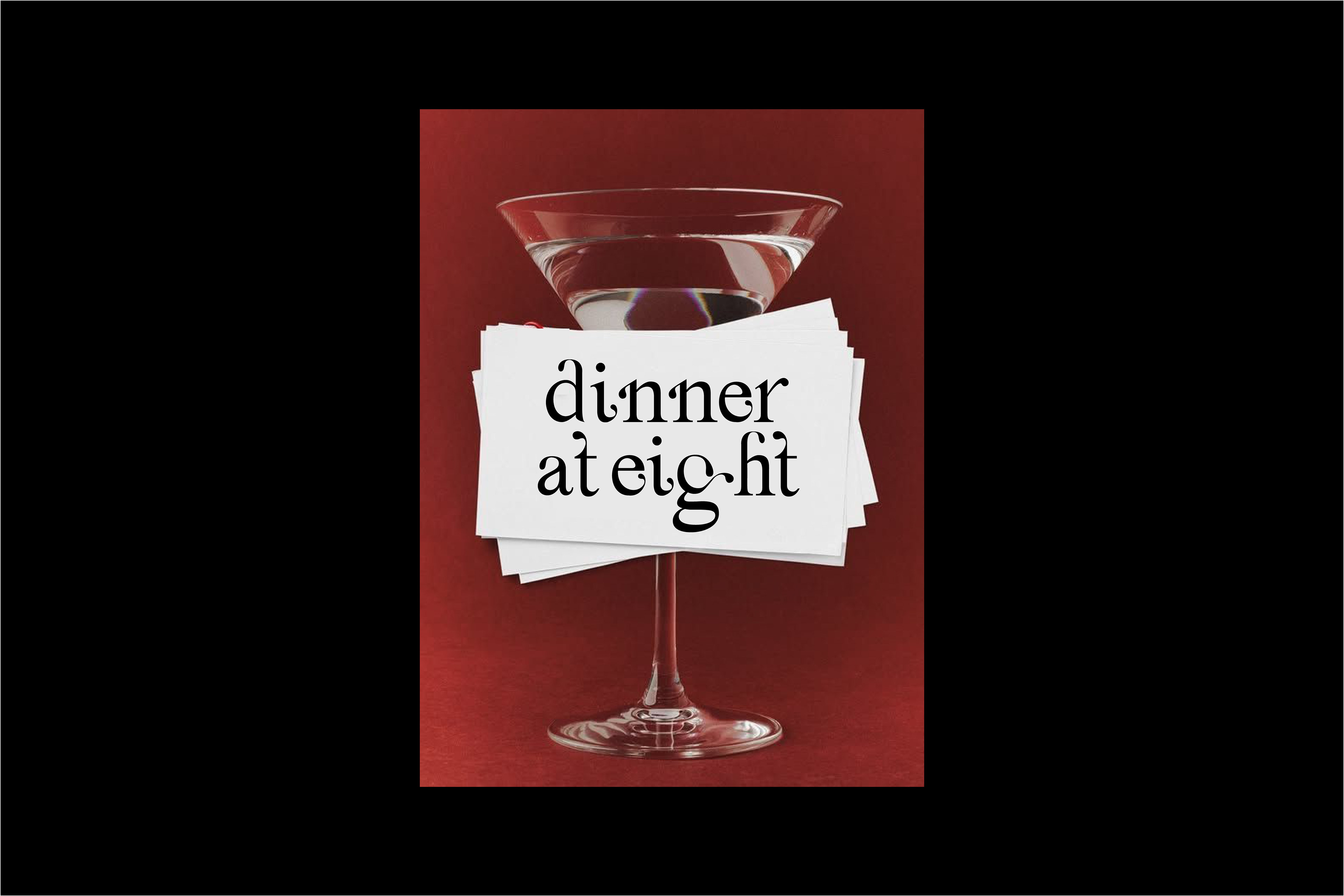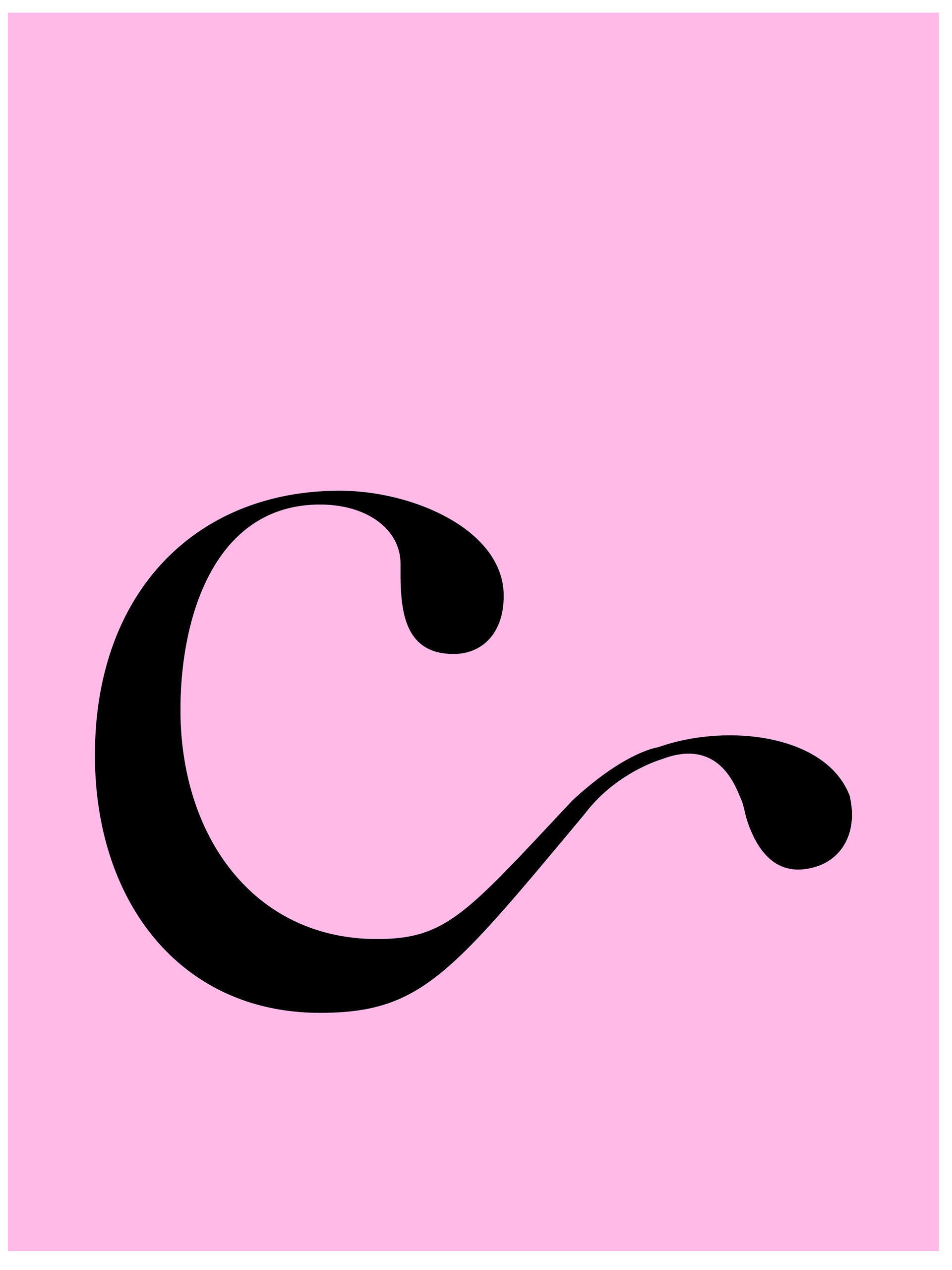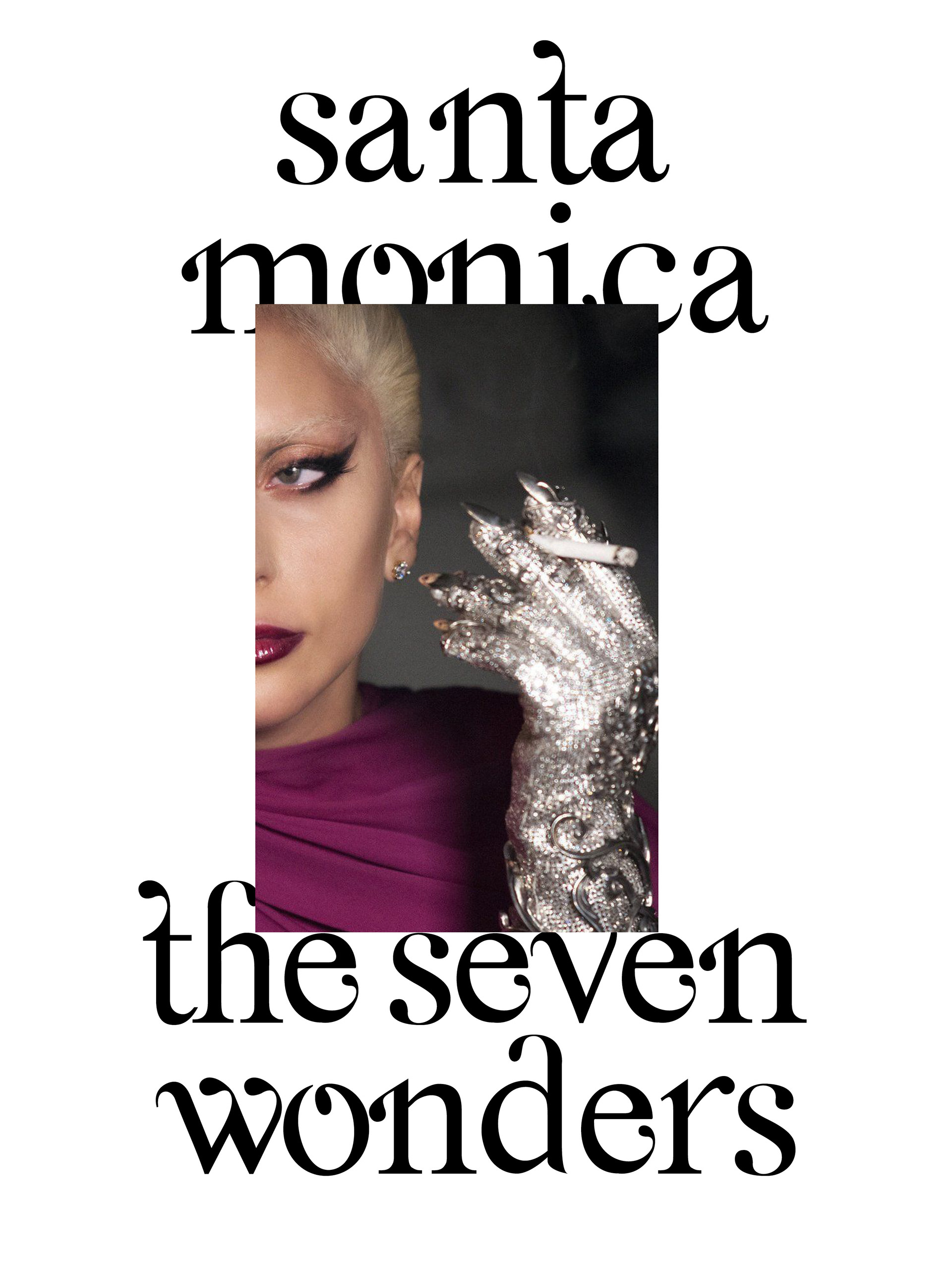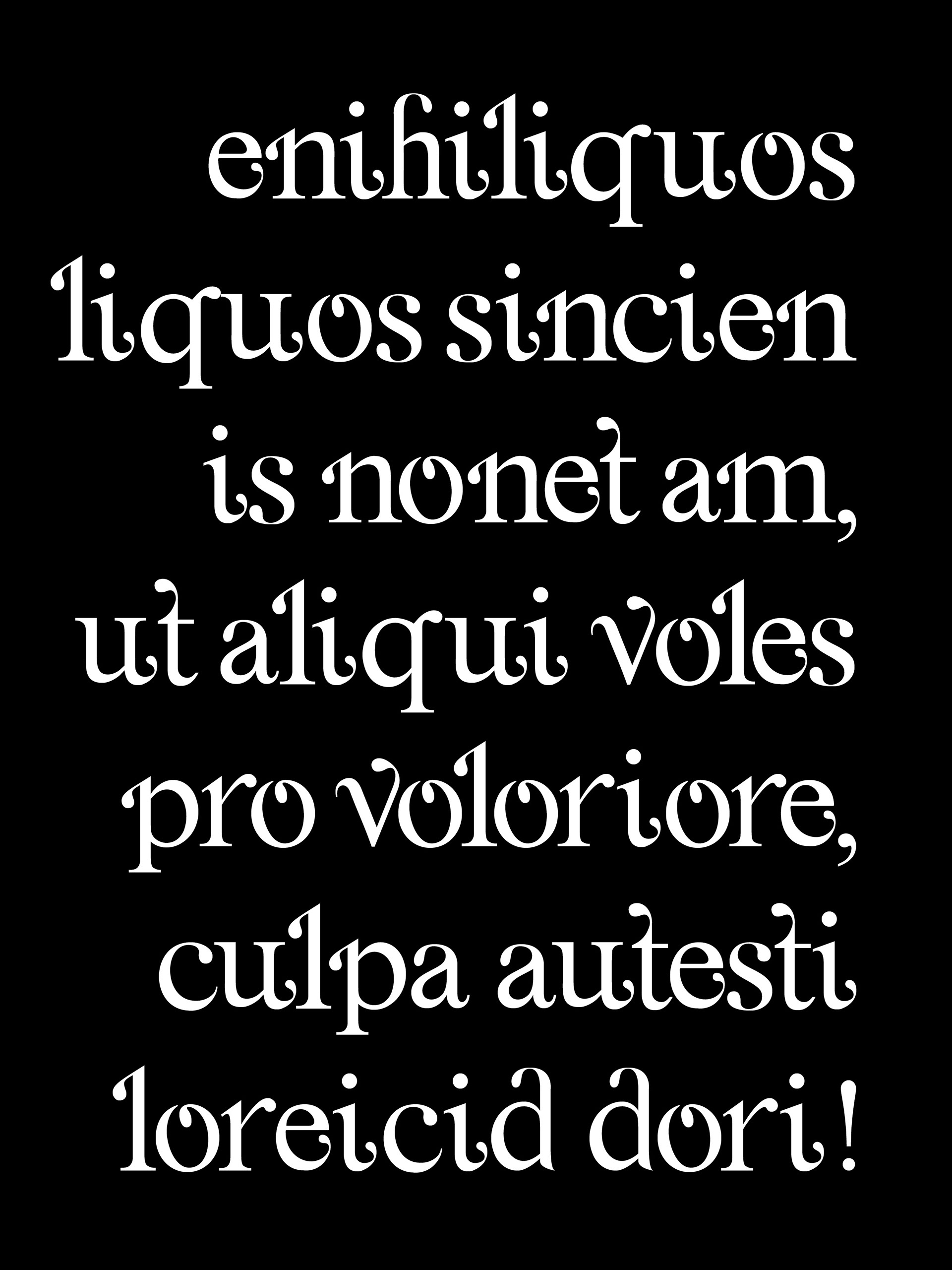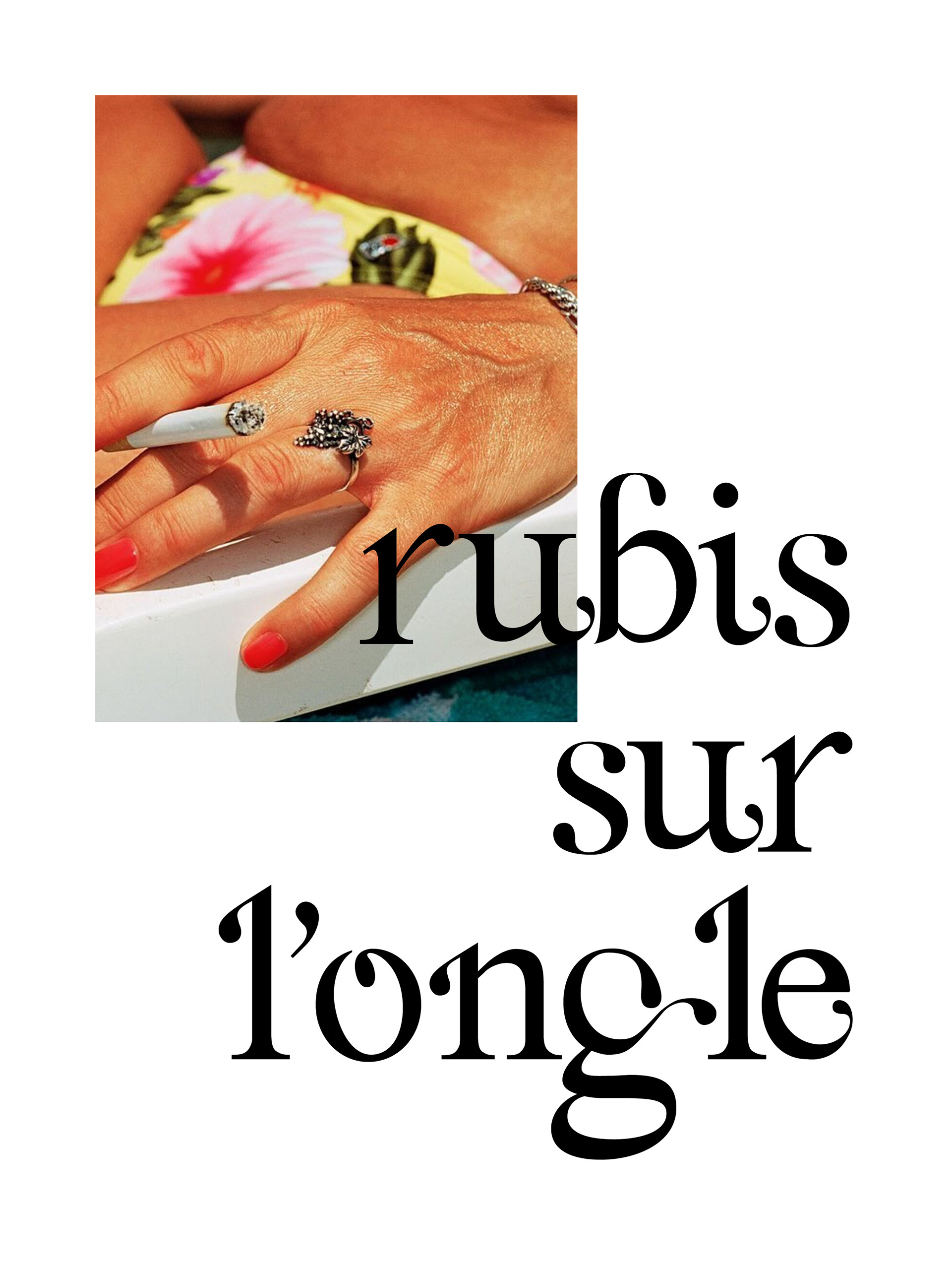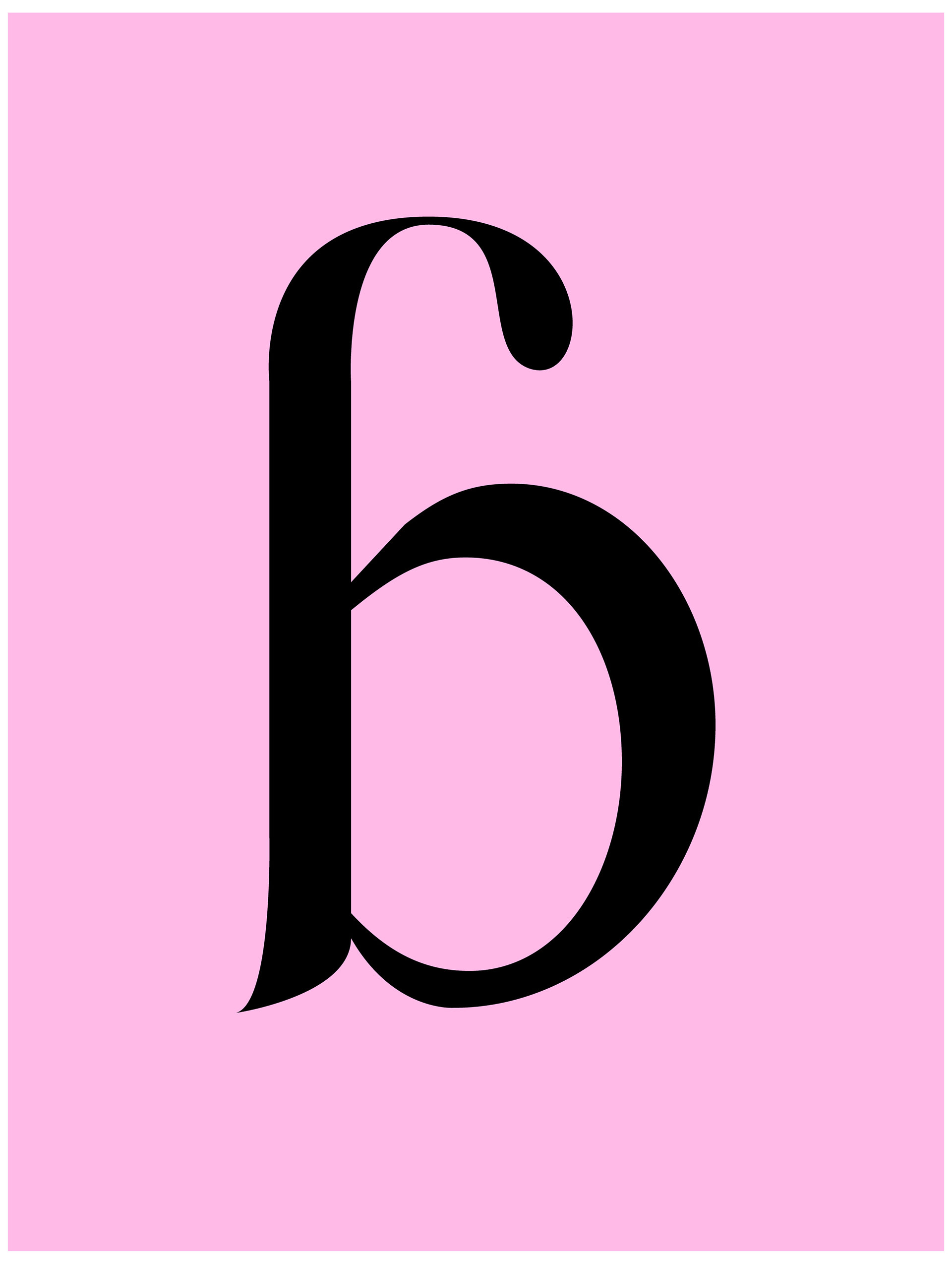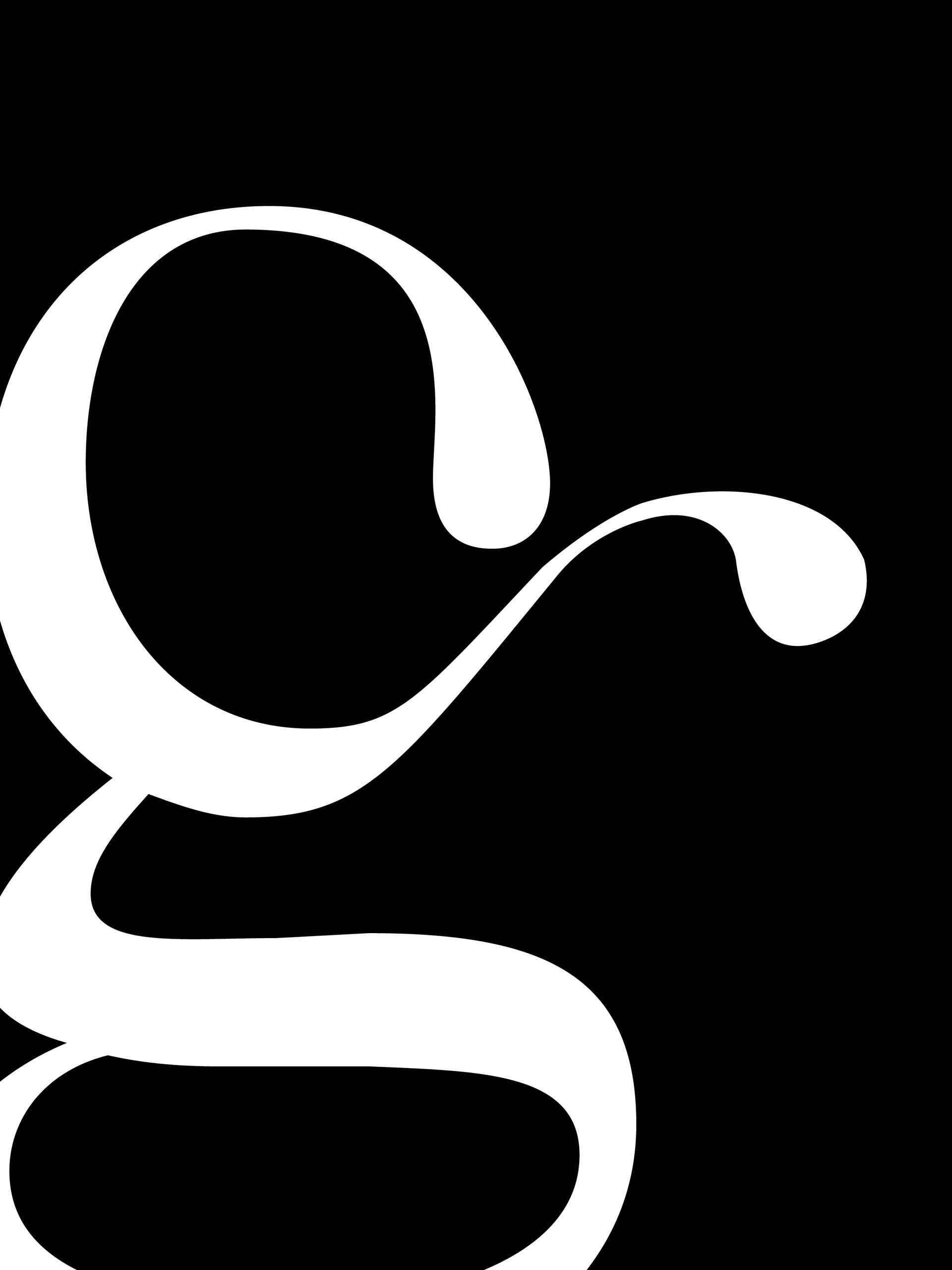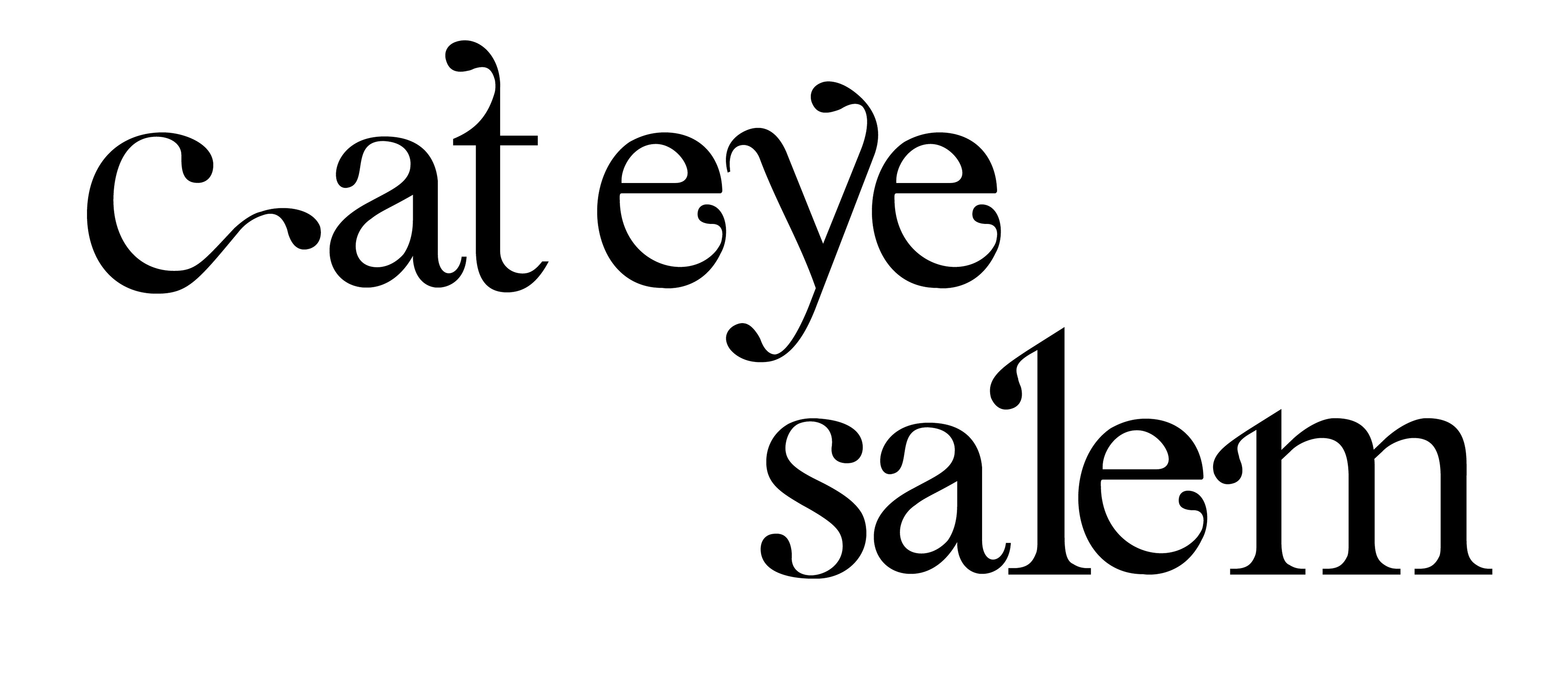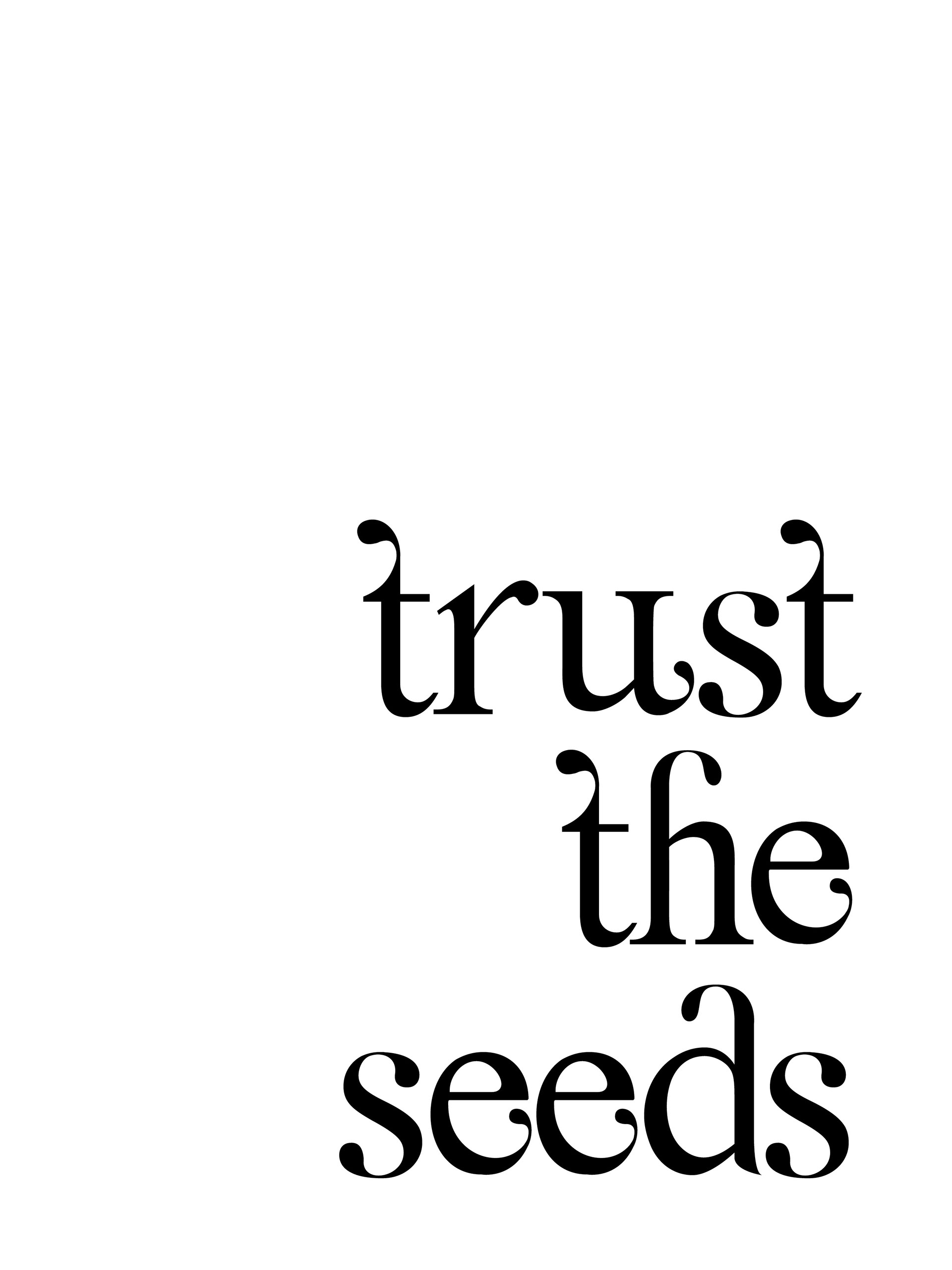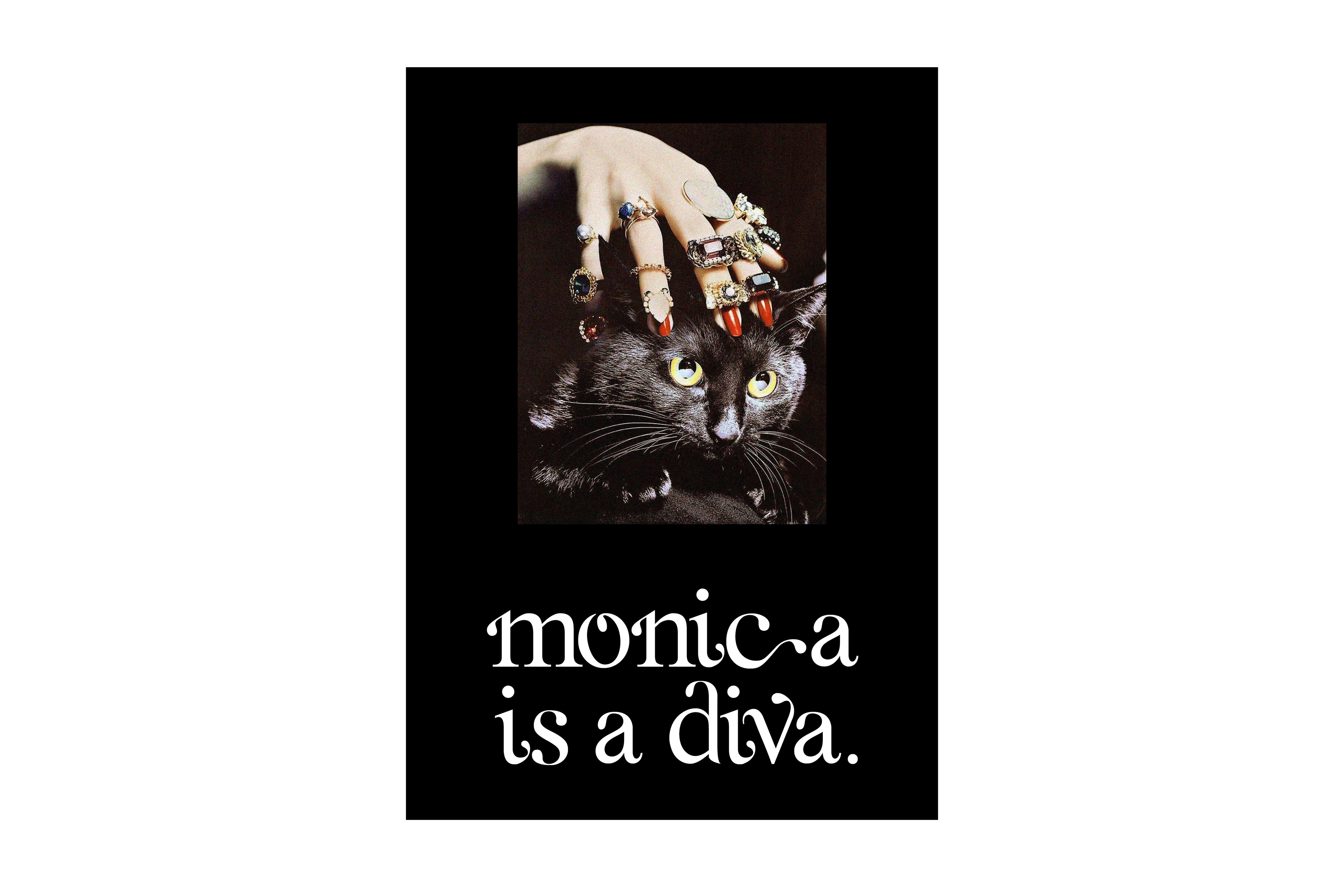
Monica est une typographie serif en bas de casse, disponible sur demande.
Inspirée par l’attitude provocatrice et féministe de certaines icônes de la pop culture des années 90,
elle assume un style sophistiqué et affirmé. Travail des gouttes, ligatures audacieuses, courbes assumées :
Monica se distingue par son caractère à la fois féminin et puissant. Elle est idéale pour des titrages de mise
en page au ton fort et assumé.
Monica is a lowercase serif typeface, available upon request. Inspired by the provocative and feminist attitude of certain 90s pop culture icons, it adopts a sophisticated and assertive style. With its drippy lines, bold ligatures, and bold curves, Monica stands out for its feminine yet powerful character. It's ideal for page layout headings with a strong and assertive tone.